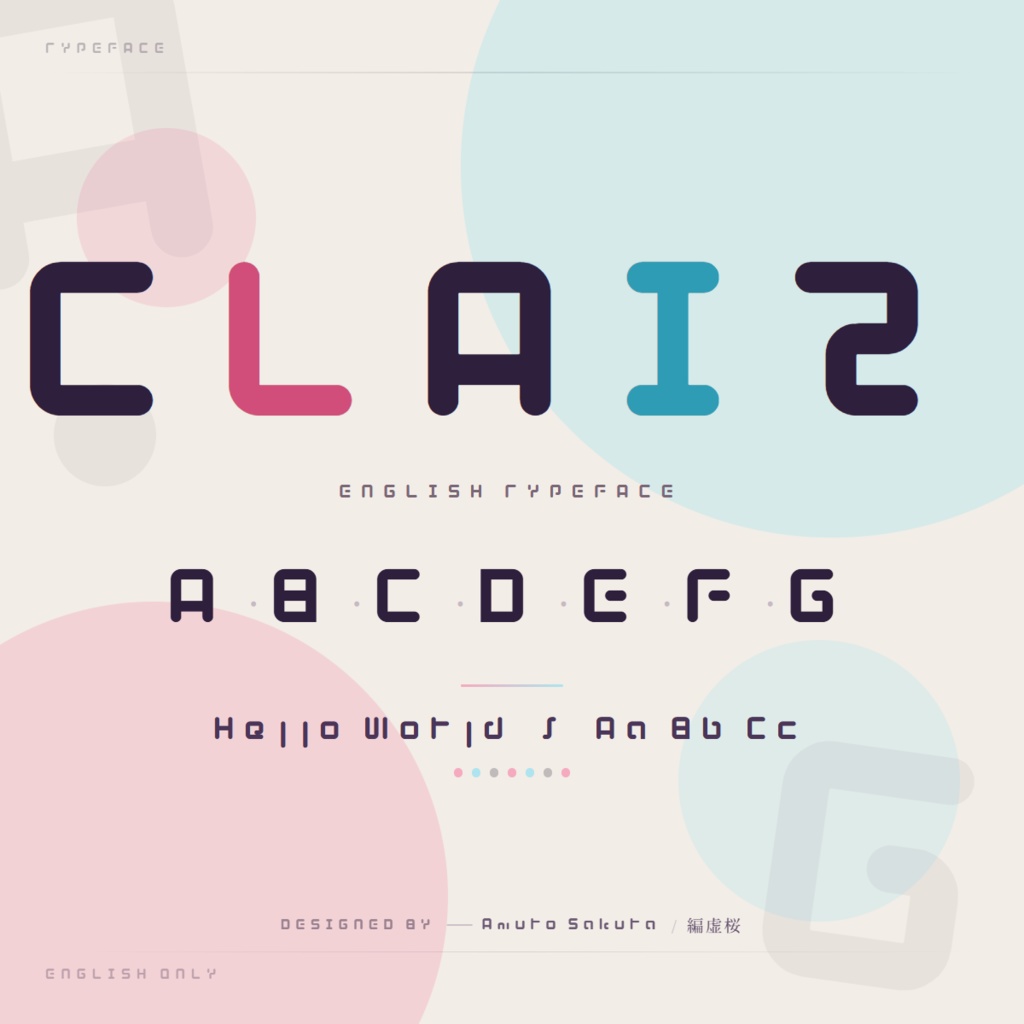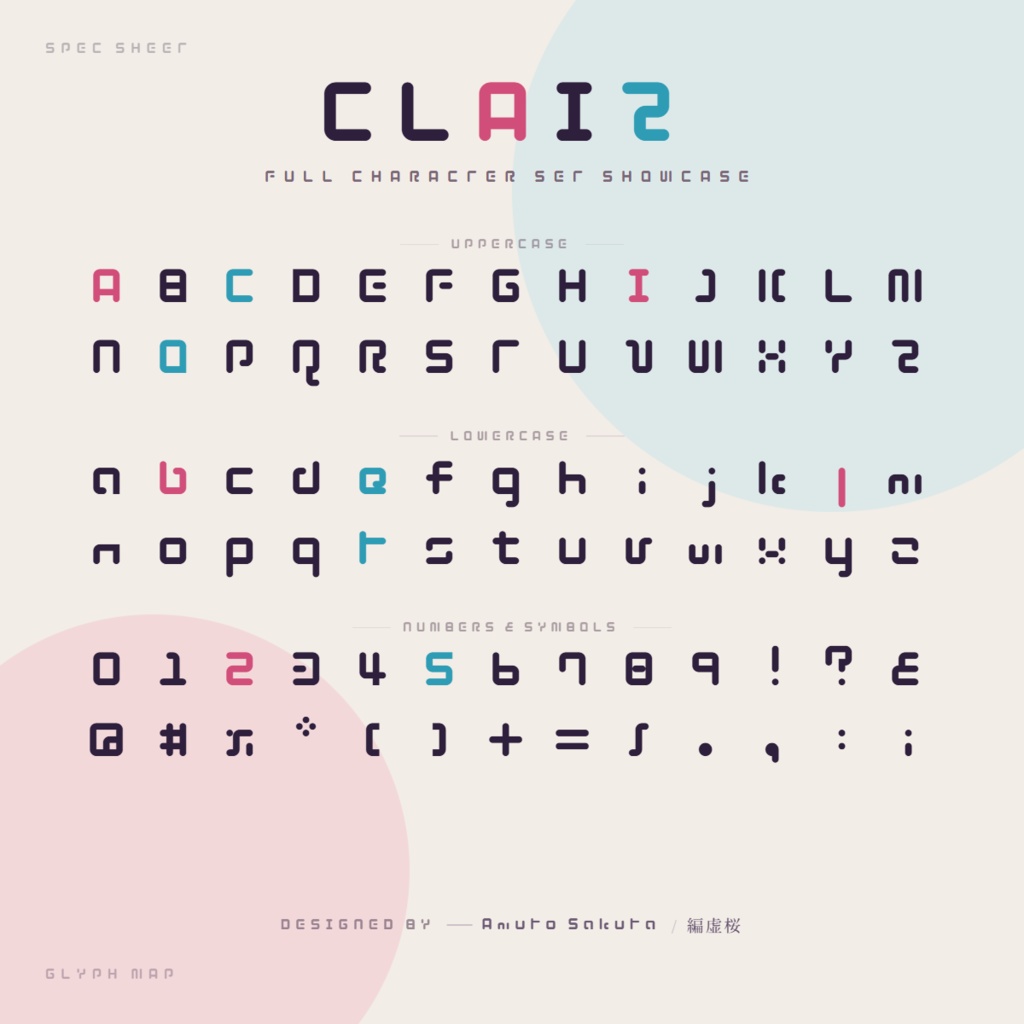
こんにちは。編虚桜です。 もちっと、ふわっと、かわいいお菓子の世界のフォント! そんなフォントを目指して、Claizを製作いたしました。
概要
Claiz-クライツは、商用利用可能なフォントで、もちっとした質感・ふわっとした感じが特徴です。 かわいい印象を与えるフォント、ふわふわな印象のフォントを製作してみよう、ということで挑戦してみました。 商品のご購入後、zipファイル同梱の利用規約 [ license.txt ] をご確認の上、ご利用ください。